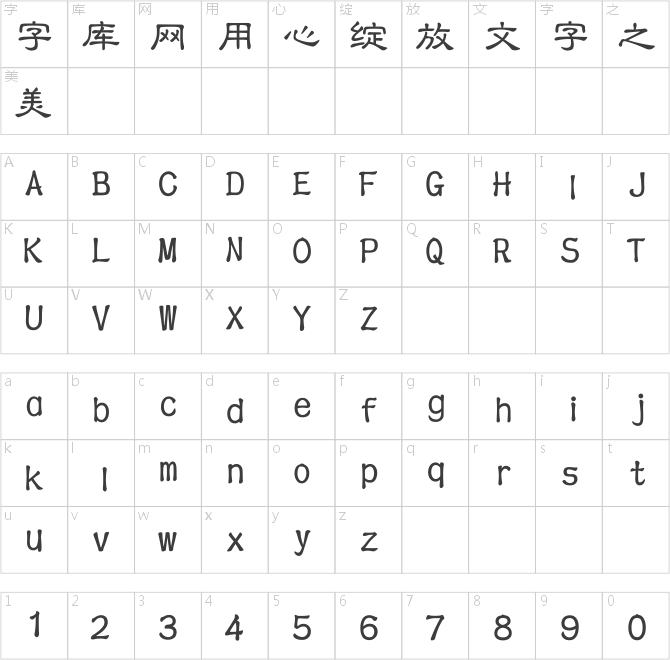
字体名称: 文鼎中粗隶简繁
文鼎中粗隶简繁
文鼎公司的中粗隶只有big5繁体版本的没有gb2312简体版本的,故本人将『文鼎中隶简』进行了加粗和轮廓线合并并并入『文鼎中粗隶big5』而形成了简易的『文鼎中粗隶简繁』原生向上兼容新版win10
20220220更新:添加日语当用汉字。一共16718个汉字。
文鼎中粗隶简繁字体字库是一款让人赏心悦目、百看不厌的中文字体,适合各类广告和产品包装设计应用,字体大小12.57MB,格式为ttf字体,上传用户是伊宁,作者/版权方为文鼎字库